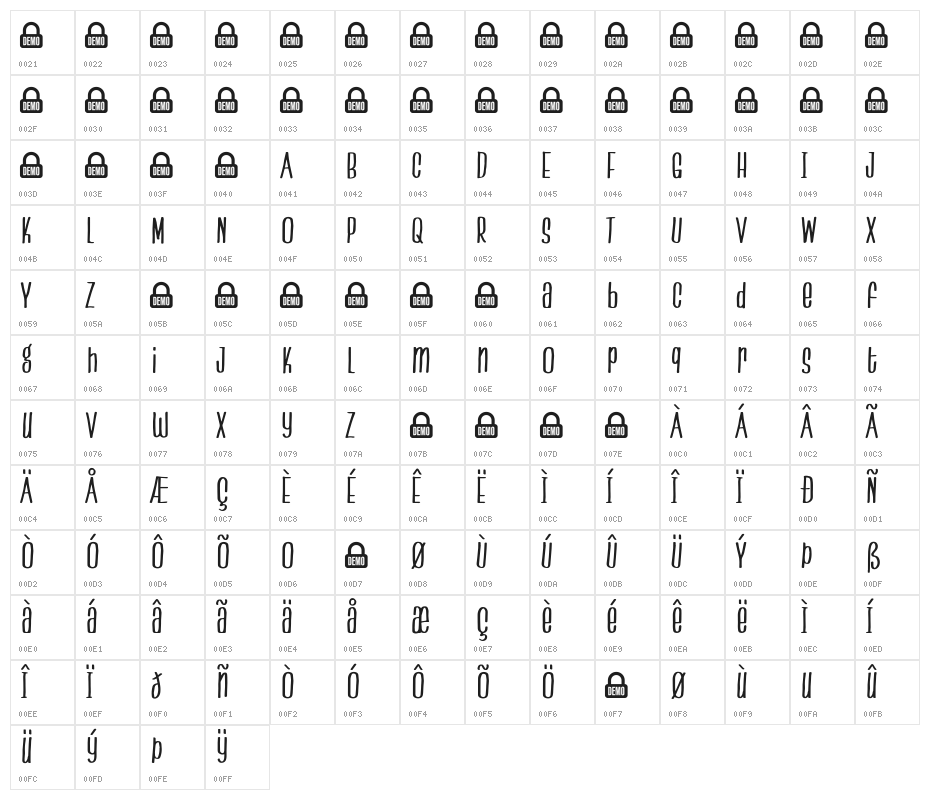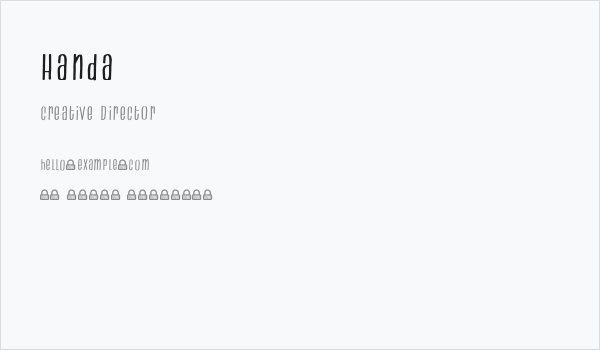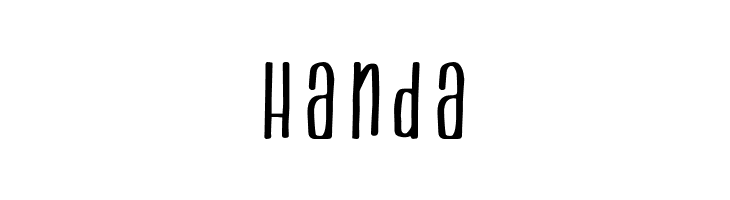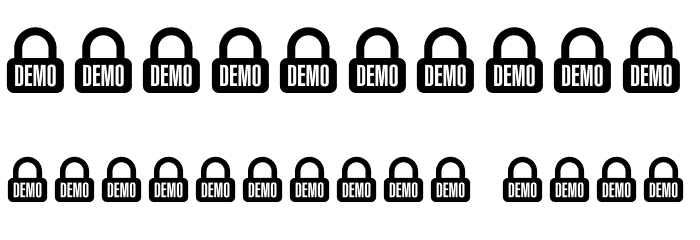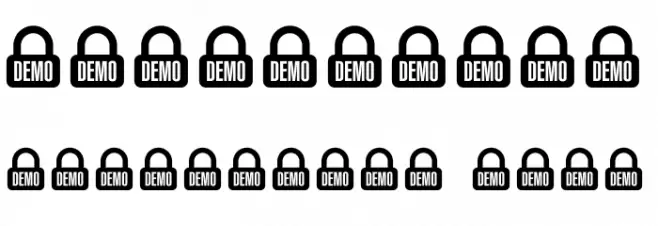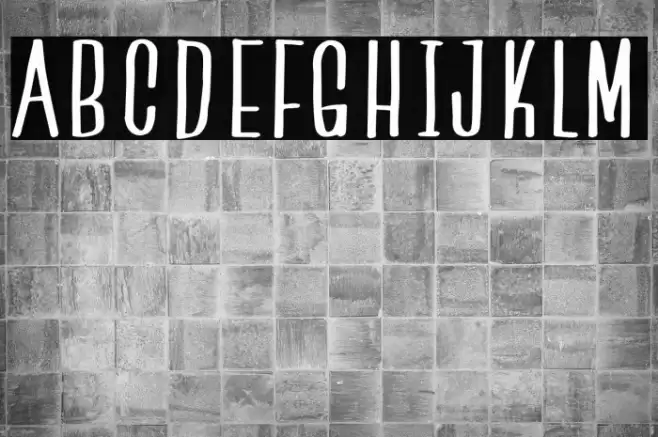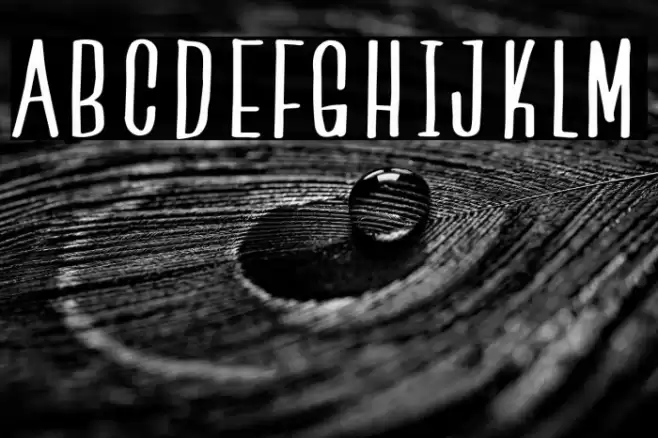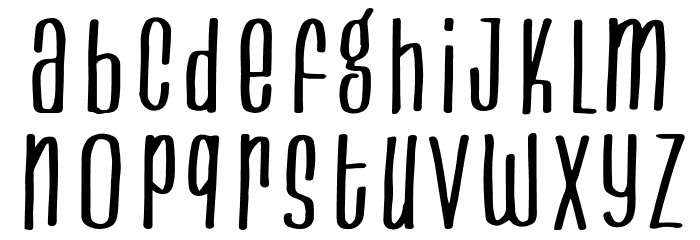
Handa Font
| Stil general | Casual, Artistic |
| Caz de utilizare | Headlines, Posters, Branding |
| Proiecte propuse | Ideal for creative projects such as posters, invitations, and branding materials that require a whimsical and artistic touch. |